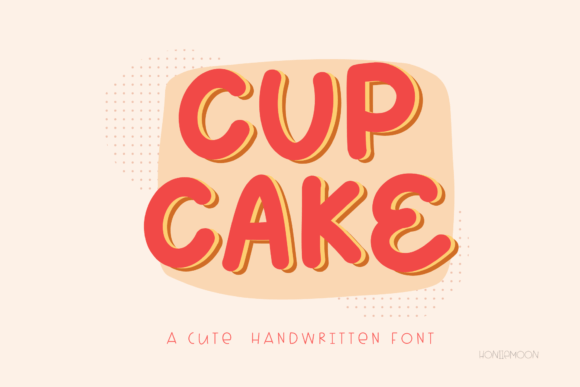
Cupcake
หากคุณกำลังมองหาเนื้อหาคุณภาพสูงเช่น Cupcake แพ็คเกจพรีเมียมนี้เป็นตัวเลือกที่ยอดเยี่ยมสำหรับโปรเจ็กต์สร้างสรรค์ของคุณ
ไม่ว่าคุณจะสร้างผลิตภัณฑ์ POD (Print on Demand) คำเชิญงานแต่งงาน หรือกราฟิกโซเชียลมีเดีย Cupcake ก็เหมาะสมอย่างยิ่ง